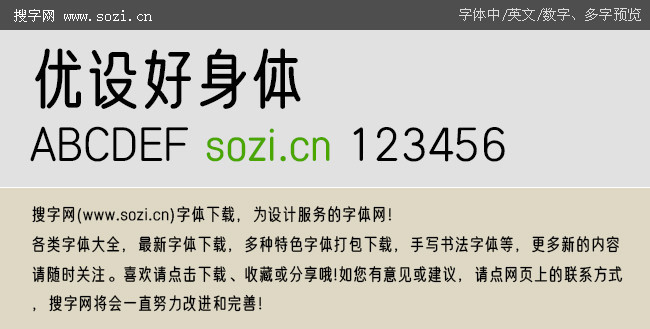
優(yōu)設(shè)好身體
搜字網(wǎng)給大家提供一款優(yōu)設(shè)好身體中文字體下載,優(yōu)設(shè)好身體是一款瘦高溫柔親和力、現(xiàn)代感極強的專業(yè)美術(shù)標(biāo)題字體。以圓體字型為基礎(chǔ),通過瘦高的字面、偏向幾何的曲線,讓整寬字體富有親和力和時尚感。適合包裝設(shè)計、書裝設(shè)計、海報設(shè)計等應(yīng)用,此字體可免費商用。